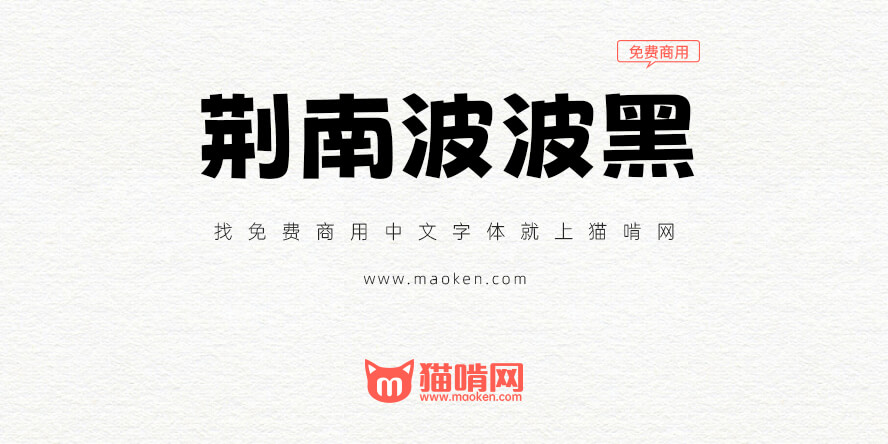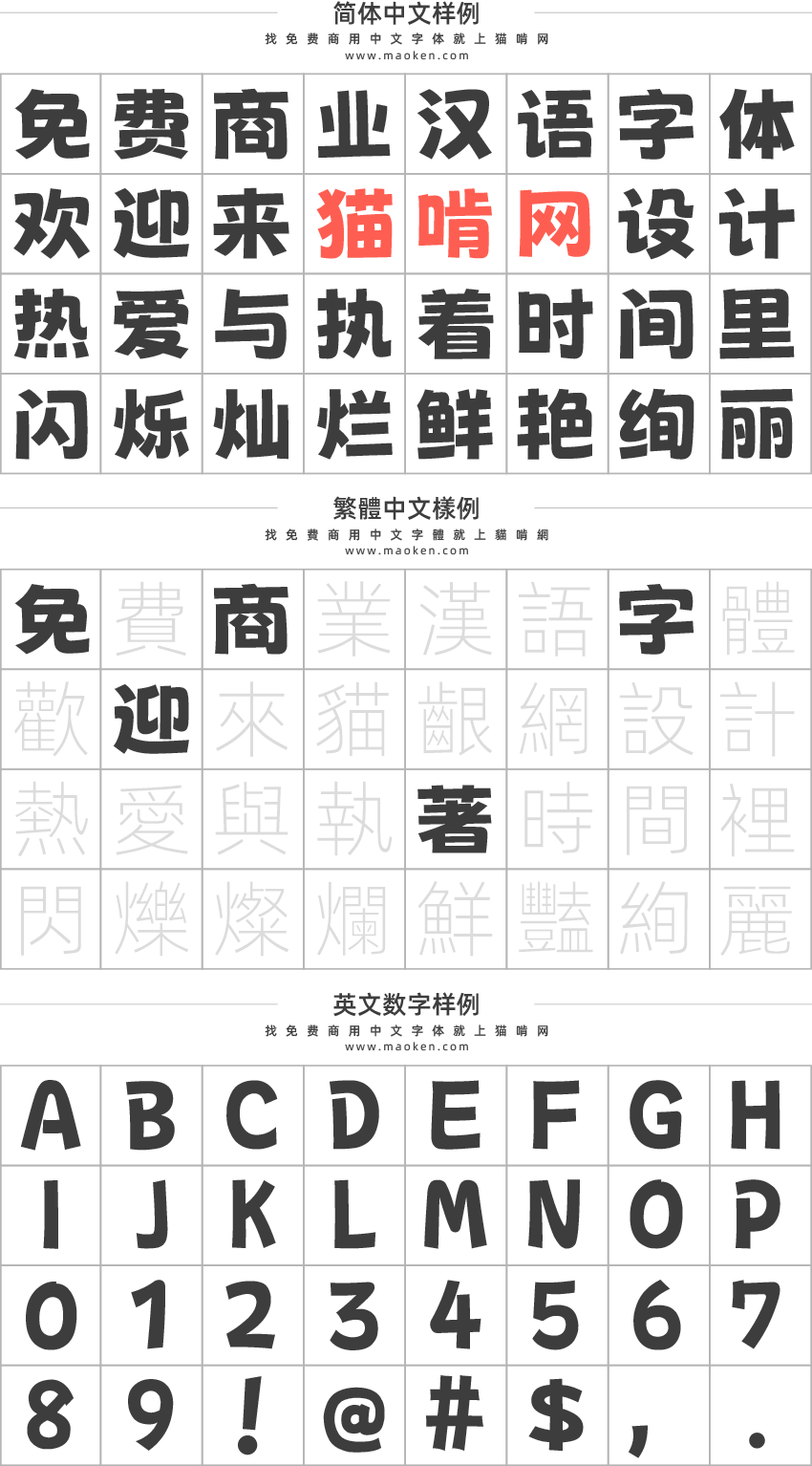
| 字体作者:荆南字坊 (中国大陆) | 字体字重:1个 |
现在的免费商用中文字体,大多以综艺体系的美术字体为主。想要找个可爱又不失实用型的标题卡通字体选择很少,几乎只能选择收费的商业字体。为了填补这个空缺,@荆南字坊特将其企划已久的「波波黑」开放为免费商用字体。
在这个平安夜,@荆南字坊呕心沥血制作的荆南波波黑预览版正式上线啦!虽然是预览版,但是却已完成5000+中文字符,已能满足大部分的设计需求啦。后续波波黑会继续完善增补,预计三款字重齐备,满足各场景需求(粗、准两款字重正在开发中)。
字体特点
荆南波波黑横竖略带波浪,不完全平直,尽显俏皮可爱。
口左上角的出头视情况而定。
精心设计的日文假名和注音符号。
流畅的曲线彰显个性动感。
字体笔画粗细排布均一合理,小字可读性较高。